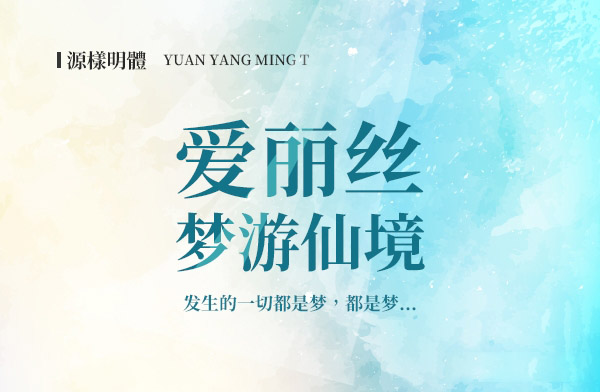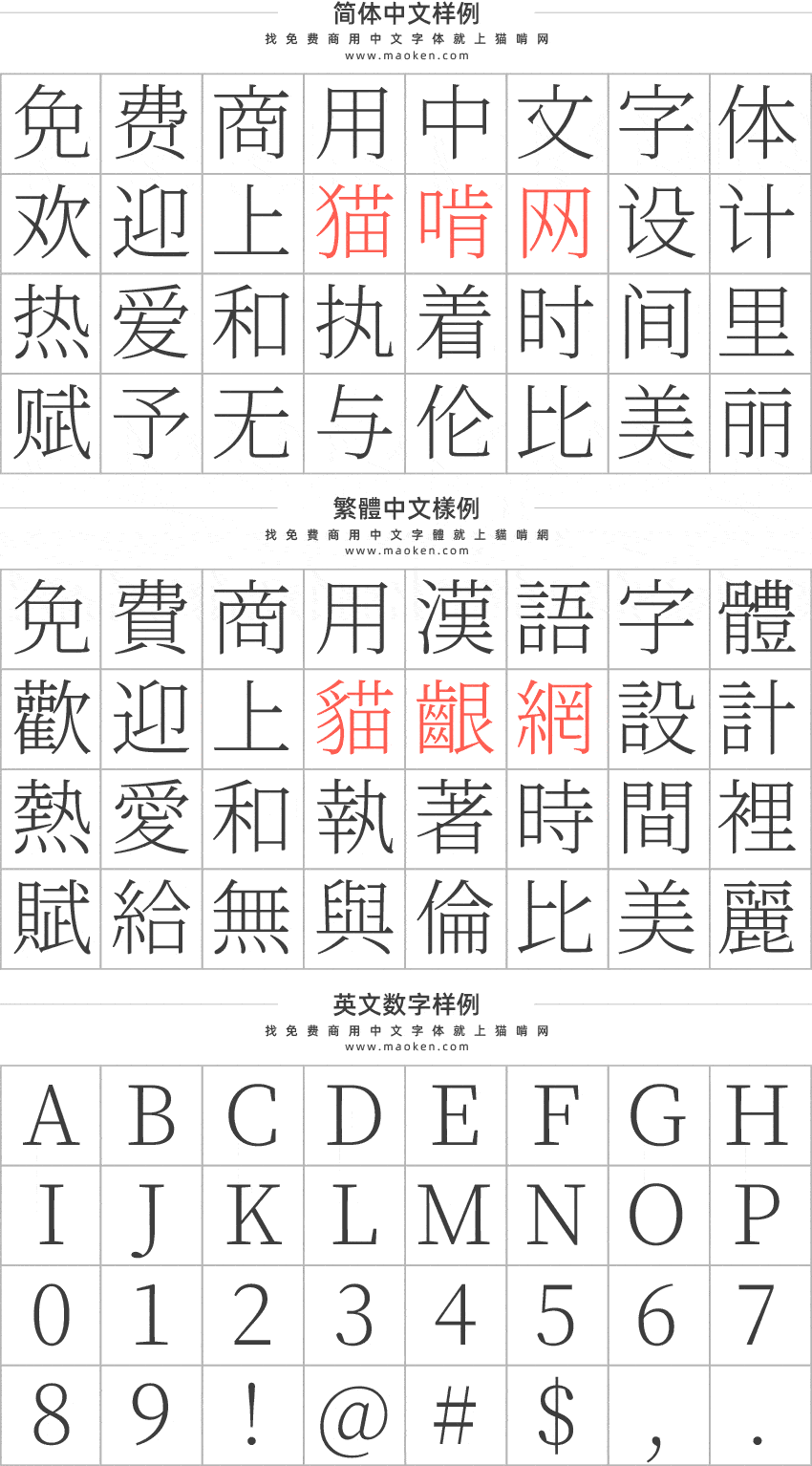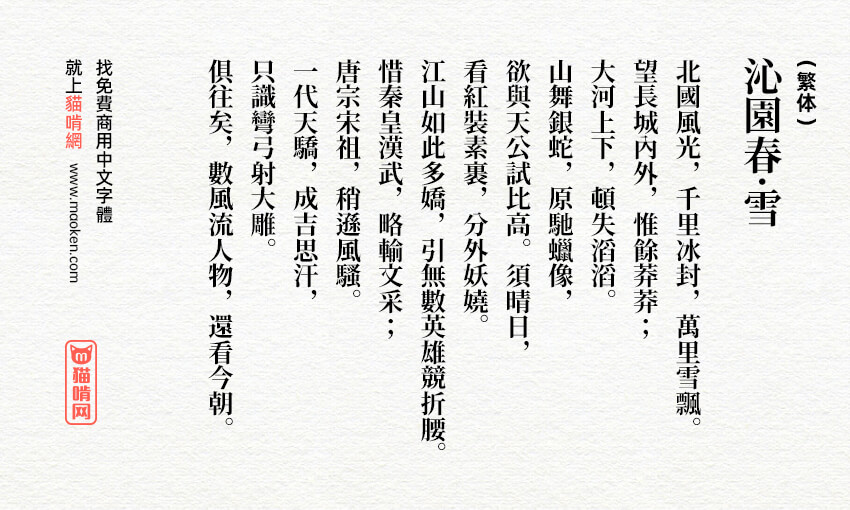
源样明朝:基于思源宋体原样直接TTF化的宋体字形 免费商用
台湾最活跃的字型社团“字嗨”管理员But Ko释出三款改造自思源宋体的繁体中文字型,开放让需要的使用者免费下载!分别为:源样明体源流明体源云明体源样明体是基于思源宋体的开放原始码中文字型。 采用思源宋体韩文(KR)版本的字符,配合繁体中文惯用的置中标点,可排版传统印刷体风格的文件。
思源宋体预设的台湾版本(TW)采用教育部标准字体,虽然适合教育用途,但不尽符合传统印刷体审美观。 例如点、挑、撇笔画太多,文件排列时的的跳动感较大。 此专案采用KR版本的字符为主,较接近传统印刷体习惯,排列感较为整齐。
Note: 本专案并没有造新的字符,所有字符都是来自思源宋体本身。所以KR版本未收录的罕用字或简化字,仍然会是TW、CN风格。
汉字不缺字
保留思源宋体所支援之所有汉字(包或日、韩文汉字与简体字),一般会用到的汉字几乎不会有缺字问题。 同时也保留了所有日文假名。(但删除了高达1万字的韩文字,有效降低字型档大小。)
Note: 本专案并没有造新的字符,简体字等当然会是CN风格。
标点符合繁体中文习惯直接使用思源宋体KR版本排中文,会有标点置于左下的问题。 此版本的标点符号仍採用繁体中文习惯,逗号、句号等都置于正中央。 并且系统能正确识别为繁体中文字型。
另外,思源宋体的标点符号如「,」「。」设定有比例宽度的压缩字宽,在Illustrator、InDesign等环境下预设会压缩50%显示。这往往会让标点显得过窄。 此版本移除了部分符号的压缩字宽资讯,让这些标点符号字宽原则上保持全形。
Ver 2.100(2024/08/22)
• 中文月、丹版,人工重否定百字常用字的写法,让写法世界统一。
• 新增KS X 1001编码范围内的韩文音节2350字与相容字母(输入法显示用)。
• 提供传统粗体模式,让软体的B按钮生效。(实作上是新增X版本,内容与B相同,附属于B版本的ttc文件中一并安装,作为R版本的粗体。otf版本未提供)
Ver 2.000(2024/07/25)
• 中文分为现代通用写法的月版(TW)与传统铅字写法的丹(TC)版,标点改回等宽。
• 日文版分割等宽版本(JP)与比例宽版本(PJP)。
• 新增jf7000当务字集与HKSCS2001汉字。
• 除 ttc 之外,另释出 otf 版本。
• 修复一些内的累积问题,如直排时破折号无置中、缺少白话字大写ᴺ。
Ver 1.500(2020/04/11)
• 支持台客语汉字
• 支持台客族语罗马拼音
• 提高注音符号品质,并支持注音直排格式
• 假名与关注类横排时比例宽
• 修改数字2、3、问号为较习惯的形式
• 改以 ttc 形式释出双语版本
Ver 1.300(2018/09/24)
• 修改部分KR版本不理想的文字对应,并统一各自文字的部件。
• 字型风格更加精致化。(三角形椭圆更圆一点。本来只有竖笔有的起笔加强,撇画也加上了。)
Ver 1.200(2018/08/19)
• 解决Word等环境直排时标点符号无法正常旋转的问题。(Word 2007 / Word 2016测试成功。转成PDF也正常。)